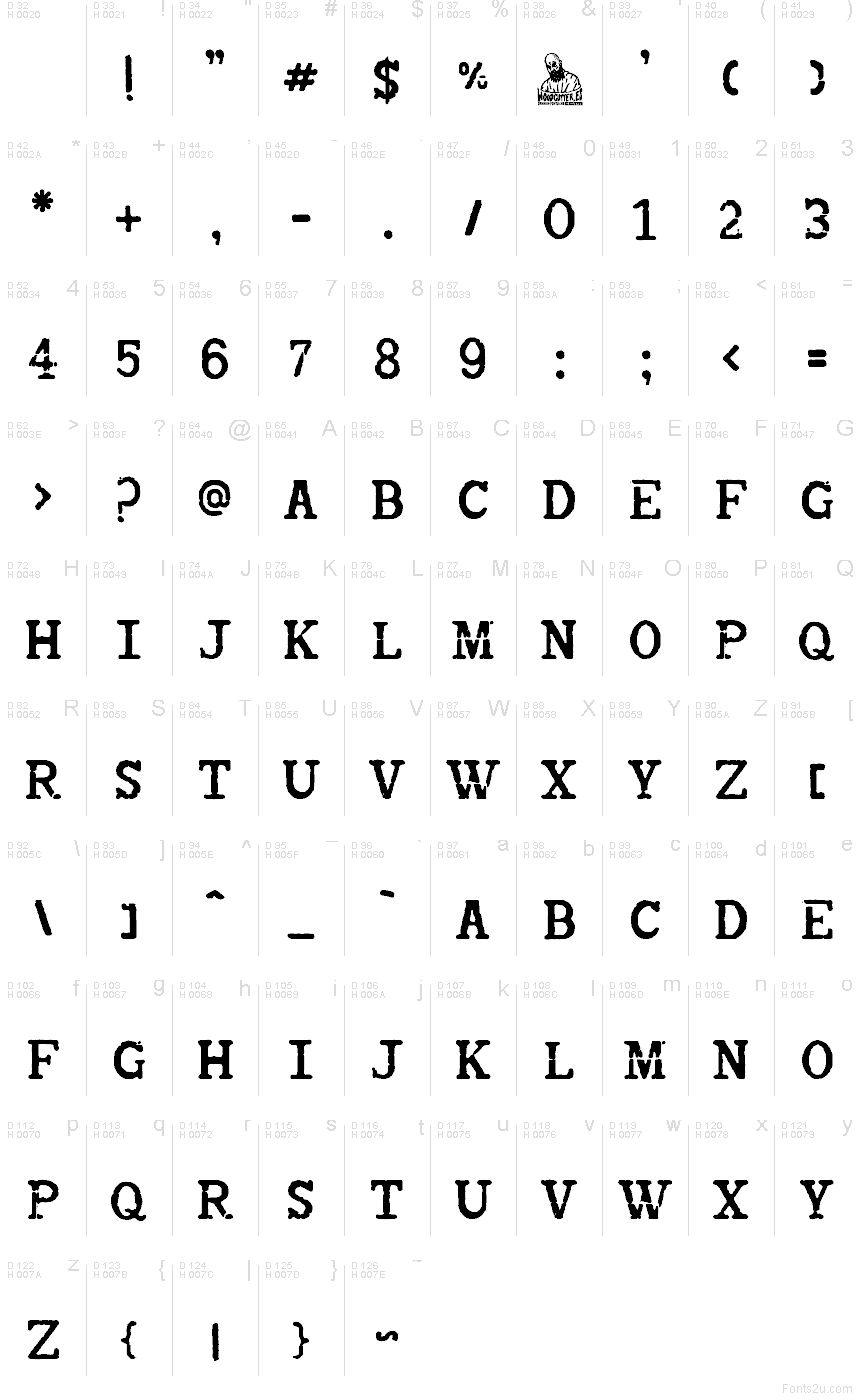
Victoria Gráfica
Woodcutter ManeroによるVictoria Graficaは、古い活版印刷のインクが滲んだような質感を再現した、無料のディスプレイスタイルフォントです。文字は重厚で使い込まれた印象で、柔らかく欠けたエッジや厚みのあるセリフは、紙に何度も強く押し付けられたかのような表情を見せます。その結果、デジタル特有の整った仕上がりではなく、無骨なヴィクトリア朝風ポスターの雰囲気が漂います。
パッケージデザインやパブの看板、書籍のカバー、タイトルカード、ポスターの見出しなど、使い古された印刷テクスチャで素早く雰囲気を演出したい場面に最適です。無料フォントとして、短いブランディングの要素やカバーのキャッチコピー、ドロップキャップ(飾り頭文字)にも適しており、ざらついた質感がそれだけで強い個性を発揮してくれます。